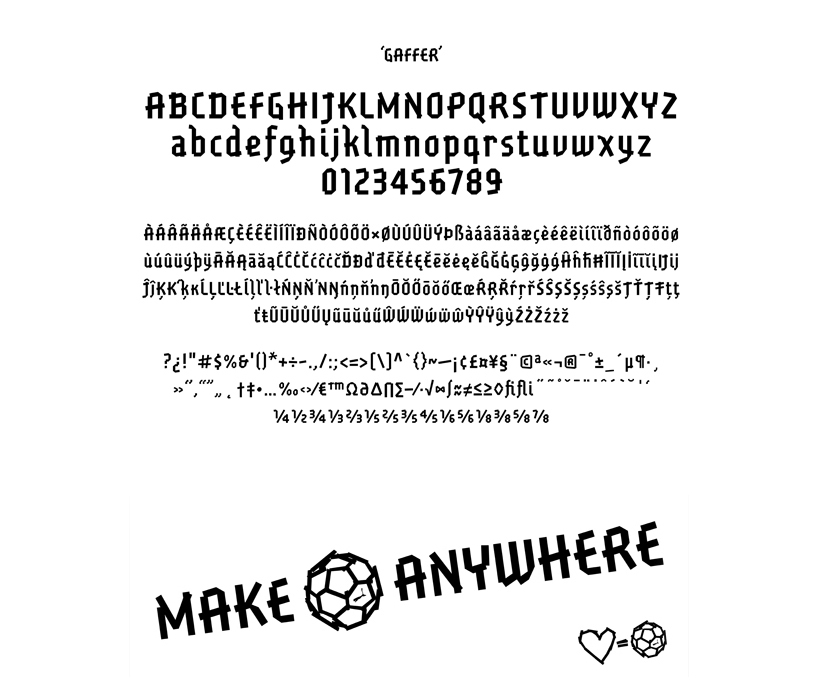
EM-Spezialfrage: Wie heißt der »Klebestreifen-Trikot-Font«
Da gerade der Krimi läuft: weiß jemand wo man diesen Trikot-Font, wie er beispielsweise bei den Italienern Verwendung findet, bekommt? Aus der Entfernung könnte man meinen er wurde aus Klebestreifen zusammen gesetzt. Bin auch für Alternativvorschläge dankbar!
GBH war sogar schon 2004 für das Typedesign der Italiener zuständig. Aber wie es aussieht, kommt man wohl an die »Gaffer« nicht ohne Weiteres ran.
Aber ich konnte Dank Deines Tipps wenigstens noch ein Alphabet bei designboom.com finden: